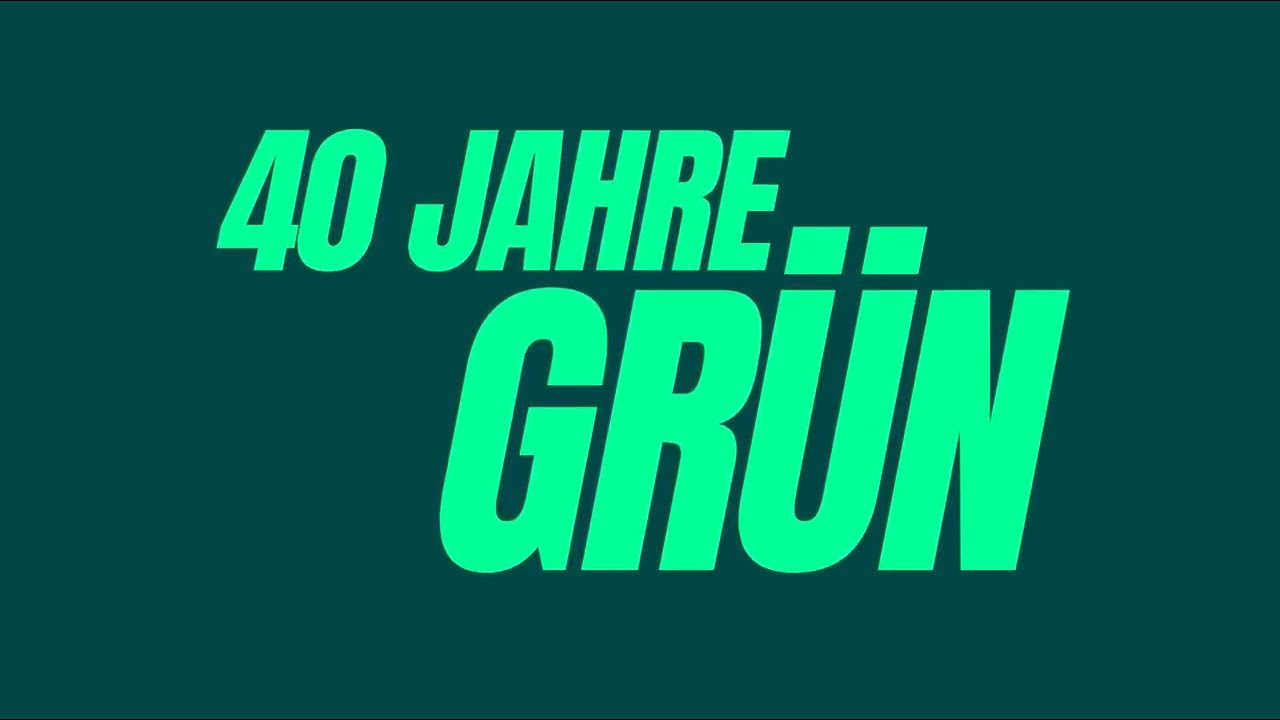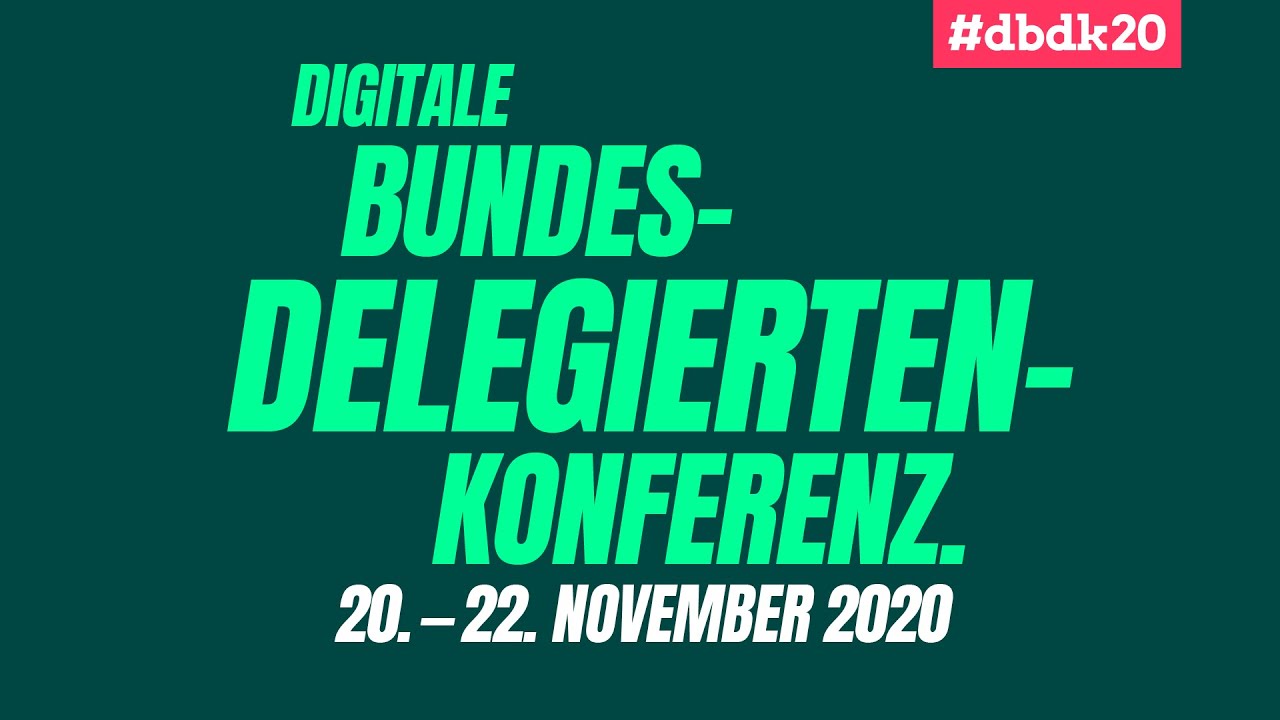
Suche kursive, condensed Sans von GRÜNEN Parteitag 2020 Visuals
ich bin verzewifelt auf der Suche nach der oblique oder italic, condensed sans-serif, die die GRÜNEN für die Visuals bei ihrem Online-Parteitag 2020 verwendet haben. Ich finde über die üblichen Font-Finder einiges, was nah dran kommt, aber nie GENAU die Schrift.
Hat zufällig jemand hier was in Petto, oder noch Identifikations-Methoden prarat, die ich nicht kannte?
Könnte eine schräggestellte Anzeigen Grotesk sein …
@bertel; Danke! Das ist auch mein closest find bisher. Ich will nicht so ganz glauben, dass sie die einfach geslanted haben. Aber vielleicht ist da ja auch noch unveröffentlichtes custom design in der Mache...
@Phoibos: Das Design, das die GRÜNEN auf dem Parteitag verwendet haben, weicht total vom bisherigen Corporate Design ab, die Futura ist es leider nicht.
Abwandlung der Futura Condensed Extra Bold
Das betrifft die Wortmarke, aber nicht den gesuchten Font.
Aber vielleicht ist da ja auch noch unveröffentlichtes custom design in der Mache...
Da die Grünen ja bisher auch gerne mal auf Freefonts gesetzt haben, könntest Du nochmal bei dafont stöbern, ob es vielleicht da diese abgewandelte Version gibt. Bei Fontsquirrel habe ich nichts gefunden.
yep, die schräg hingebogene Anton passt zu 100%, hab’s grad mal getestet.
Ist das Originalkerning tatsächlich so eng laufend oder wurde da beim Satz eingegriffen bis dann den DELEGIERTEN GIER unterstellt wird?
Ich fürchte das ist die Anton regular schräg hingebogen
@pürsti JA! Das ist sie! Tausend Dank! Das Kerning ist tatsächlich im Original so.
Aber: Grrr - warum können die in so einer Größenordnung der Anwendung nicht etwas mehr Quality wollen...